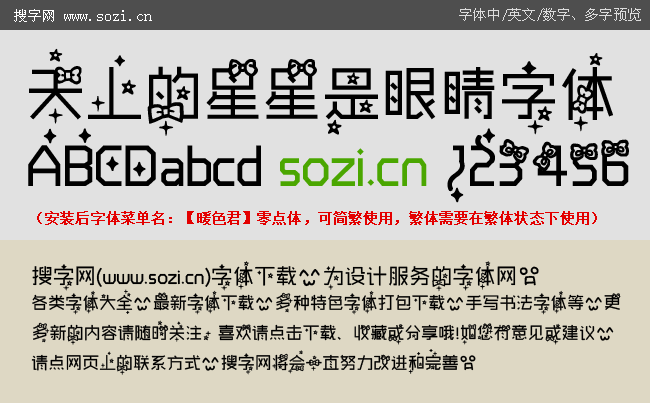
天上的星星是眼睛字體
搜字網(wǎng)給大家提供一款卡通手機(jī)中文字體下載。字體名叫天上的星星是眼睛字體,這款手機(jī)中文字體是一款黑體風(fēng)格的藝術(shù)字體,并且在筆畫間嵌入了大量的星星與蝴蝶結(jié)卡通圖形,該中文字體趣味性強(qiáng),又保持了文字的識別度,非常適合喜歡卡通的朋友在手機(jī)上安裝使用。